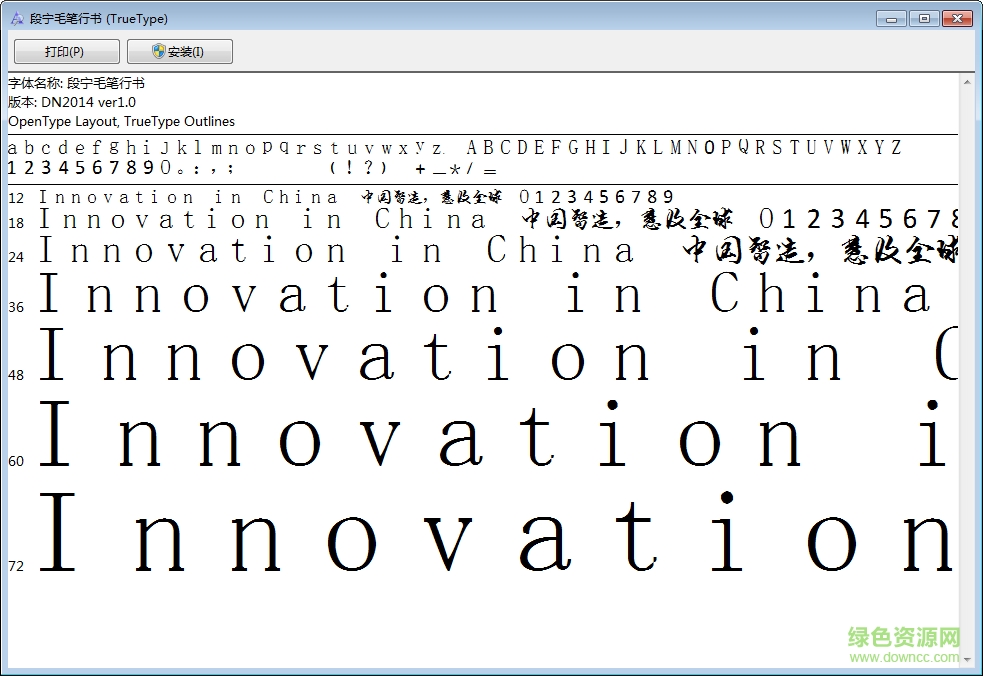
軟件介紹 軟件標(biāo)簽: 段寧毛筆行書 行書 字體 段寧毛筆行書是一款非常好看的字體,融入行書的元素,使得字體變得非常的洋洋灑灑,獨(dú)具個性,支持中文、英文和阿拉伯?dāng)?shù)字,線條十分流暢,喜愛的朋友趕快到綠色資源網(wǎng)下載體驗(yàn)吧!官方介紹段寧毛筆行書字體充滿了流線感,字體結(jié)構(gòu)十分的清晰,主要適用于廣告設(shè)計、藝術(shù)繪畫、書籍印刷等方面。使用方法1.直接將字體復(fù)制到C:\WINDOWS\Fonts。2.控制面板/字體/文件/安裝新字體。 軟件截圖 上一張下一張(1 / 1) 安裝詳細(xì)截圖 猜你喜歡 行書字體 毛筆字體 行書字體 行書字體包括了鋼筆字行書字體大全、硬筆行書字體等,是一種介于楷書和草書之間的字體。為什么這樣說?因?yàn)樾袝煮w既有草書的流暢感,又有楷書的端正感,可以說,行書結(jié)合了草書和楷書的特點(diǎn),形成了獨(dú)特好看的行書字體。喜歡的朋友,趕快下載體驗(yàn)吧! 查看更多>> 繁體行書字體 9.76M/中文/4.0/免費(fèi)版下載 winman tun10011字體 17.57M/中文/6.6/下載 南構(gòu)嘉飛行書字體 10.00M/中文/6.6/下載 c g流麗行書體繁/簡 4.39M/中文/5.0/下載 北方行書簡體 2.63M/中文/7.2/下載 qxyingbixing 1.26M/中文/8.0/下載 毛筆字體 毛筆字體是一類同硬筆書法完全不同的書寫方式,毛筆方法種類繁多更顯飄逸與古典氣質(zhì),是中國人的經(jīng)典傳承,無論是用于對聯(lián)、藝術(shù)設(shè)計還是門匾都顯示深沉莊重,綠色資源網(wǎng)小編整理了毛筆書法字體大全,歡迎大家下載體驗(yàn)! 查看更多>> plume毛筆字體 416KB/中文/10.0/下載 衡山毛筆行書 4.16M/中文/10.0/下載 金梅新毛筆草楷 3.41M/中文/10.0/下載 金梅新毛筆隸書 2.34M/中文/10.0/下載 味わい毛筆pro字體 35.00M/中文/6.0/下載 葉根友毛筆行書2.0版 1.09M/中文/1.7/免費(fèi)版下載 其他版本下載 標(biāo)題 大小 更新日期 下載 下載地址 電腦版 段寧毛筆行書 點(diǎn)擊報錯 軟件無法下載或下載后無法使用,請點(diǎn)擊報錯,謝謝! 關(guān)閉報錯反饋 請描述您所遇到的錯誤,我們將盡快予以修正,謝謝! *必填項(xiàng),請輸入內(nèi)容 本類最新 dreamweaver字體庫 首爾南山體字體 v1.06 官方版 潮字社風(fēng)云簡ttf 潮字社凌渡鯤鵬簡體字體 潮字社曾玉波手書簡字體 微博慧心字體 相關(guān)文章 Photoshop字體安裝使用方法和技巧 如何解決“無法新增字體”問題 Win 7系統(tǒng)安裝字體方法 網(wǎng)頁字體大小設(shè)置方法 怎么改網(wǎng)頁字體大小 在Linux系統(tǒng)中安裝字體的幾種方法 windows7字體顯示問題:打開某些程序的時候顯示的是亂碼 用戶評論 熱門評論 最新評論 發(fā)表評論 查看所有評論(0) 昵稱: 請不要評論無意義或臟話,我們所有評論會有人工審核. 字?jǐn)?shù): 0/500 (您的評論需要經(jīng)過審核才能顯示)